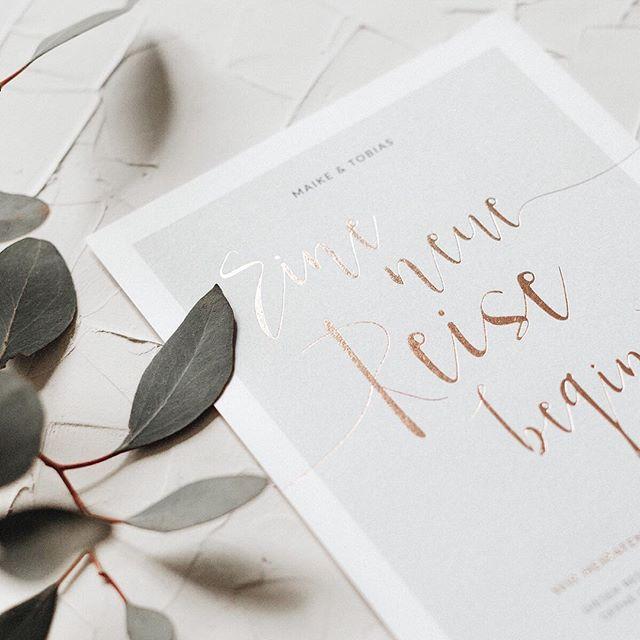
Schriftarten für eine Menükarte gesucht
ich bin auf der Suche nach diesen Schriftarten für eine Menükarte. Bei Instagram habe ich unter folgendem Link: https://www.instagram.com/papierformat/?hl=de das beigefügte Bild gefunden.
:tuschel: Ich kann solche Schriften ja nicht mehr sehen, und wirklich schön fand ich bisher die wenigsten. Man kann kalligrafisch so schöne Sachen machen … :-?8-)
Bessere, elegantere und lebhaftere Handschriften findet man z. B. bei Laura Worthington oder Sudtipos :nicken:
Beim Nochmaldrübergucken habe ich überlegt, was mir nicht gefällt 🤔
Da wäre z. B. Das Sicherheitsnadel-e, das Pieksen spüre ich quasi; und dieses ungelenke s und die gequälten Buchstabenübergänge …